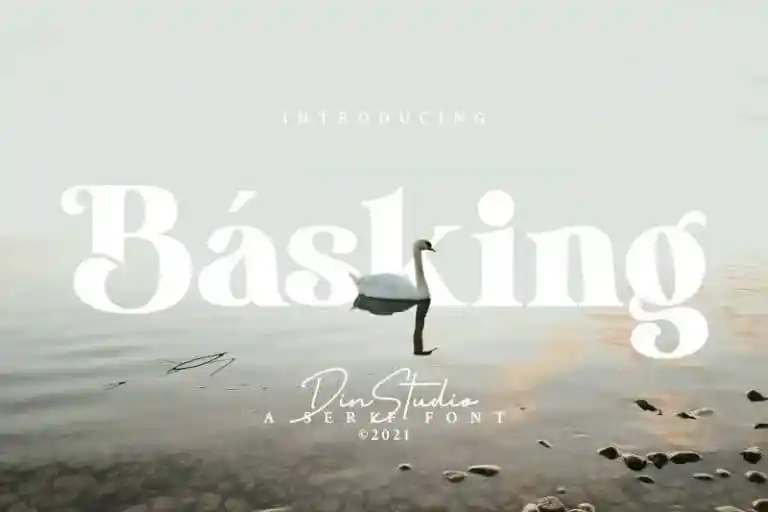
Basking Serif Font
A Basking Serif Font é uma fonte serif bold que se destaca por sua elegância e força. Elegante para uso em branding e identificação visual, ela traz aos projetos um charme sofisticado e profissional sem perder a personalidade única do seu projeto. Com uma tipografia serif, você pode criar mensagens de impacto nas redes sociais ou em designs de moda, e ainda agregar um toque exclusivo ao design impresso de citações e embalagens. Suas linhas leves mas firmes se adaptam perfeitamente a qualquer tipo de conteúdo, tornando-a uma fonte versátil para vários projetos. Com Basking Serif Font, você pode criar um estilo único que destaca seu trabalho entre tantos outros.